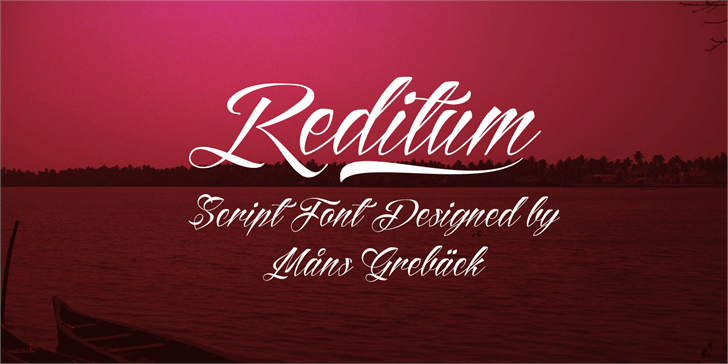
A fonte Reditum Font é uma criação única do designer Måns Grebäck lançada em 2014, ideal para quem busca adicionar um toque personalizado a suas projetos digitais. Esta elegante e versátil fonte script foi projetada com nuances cuidadosamente elaboradas, criando linhas finas que se movem sutileza e uma tonalidade delicada que traz vida às palavras. Ideal tanto para textos profissionais quanto para uso pessoal, a Reditum Font é uma ótima escolha para quem busca um toque elegante em seu design gráfico. É especialmente adequada para aplicativos de escrita digital e sites onde o equilíbrio de texto e imagem é fundamental. Esta fonte personal use only está disponível para download por designers interessados que buscam adicionar uma marca única a seus projetos, sem comprometer seus direitos autorais.